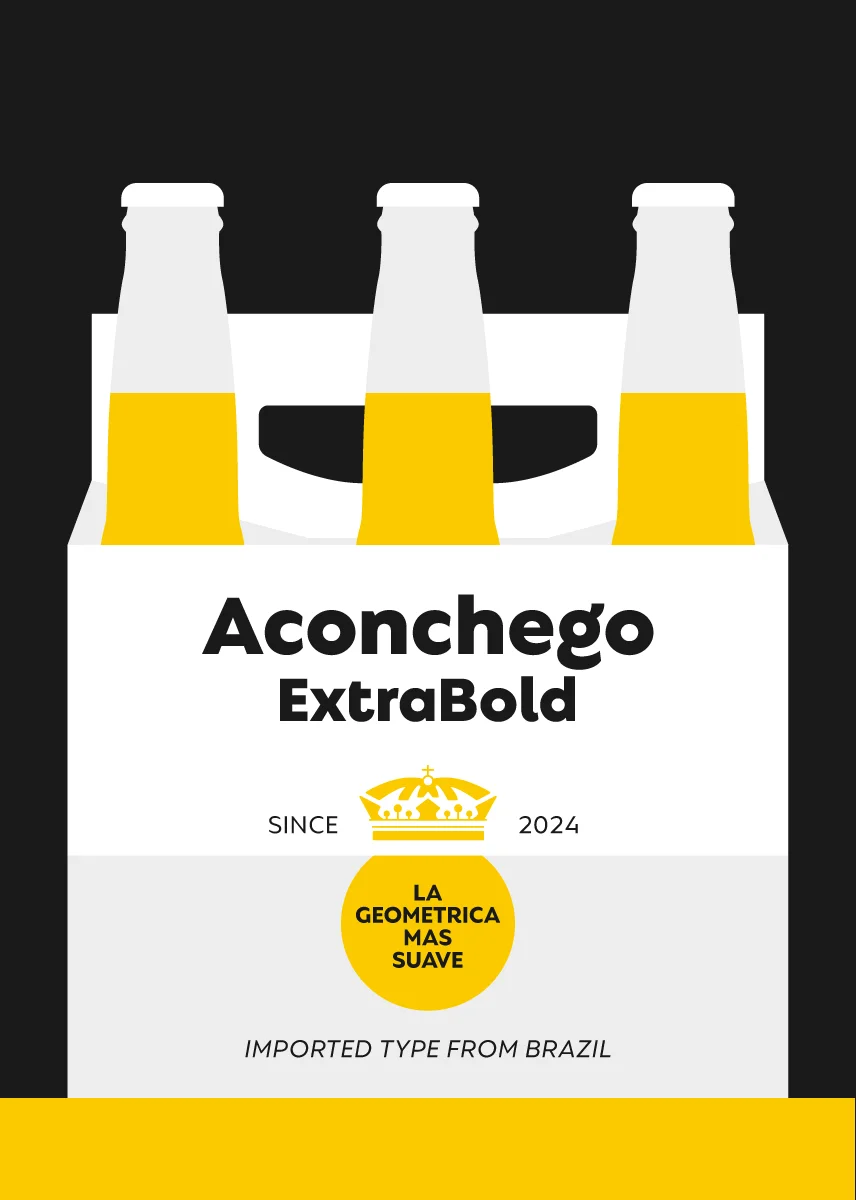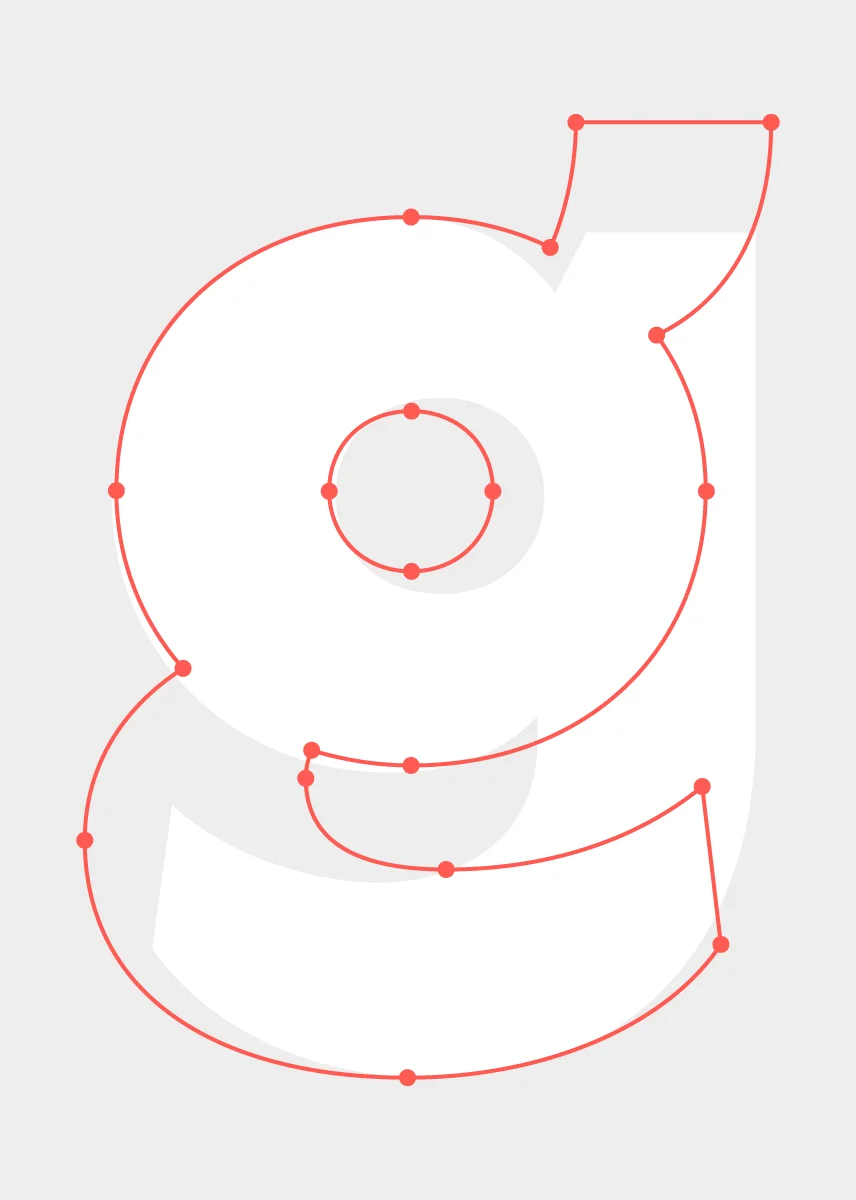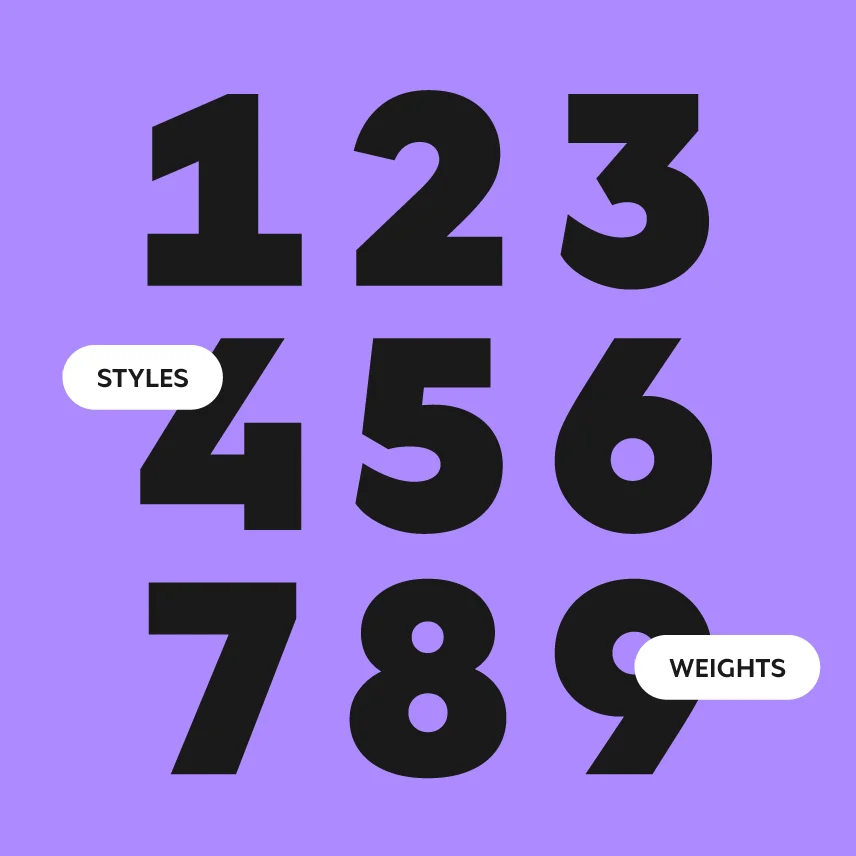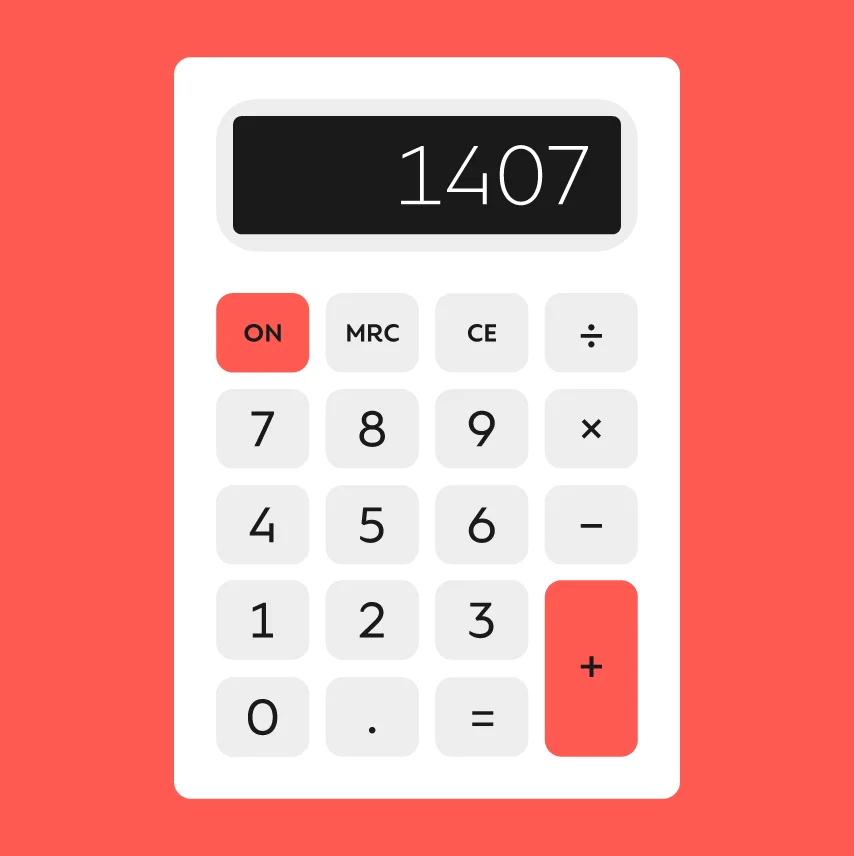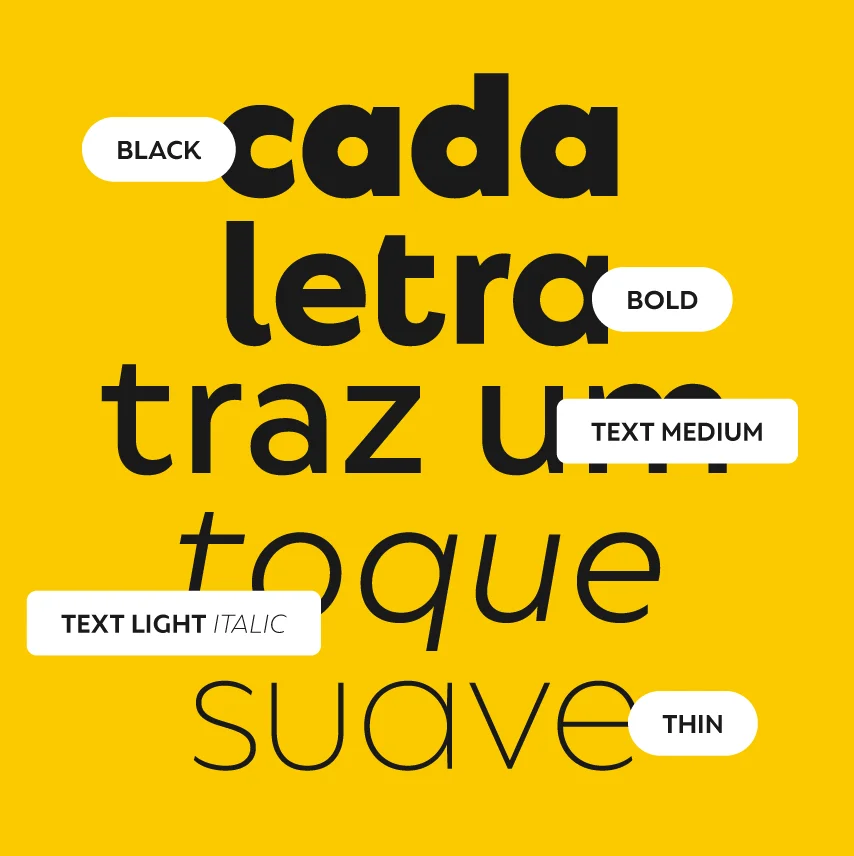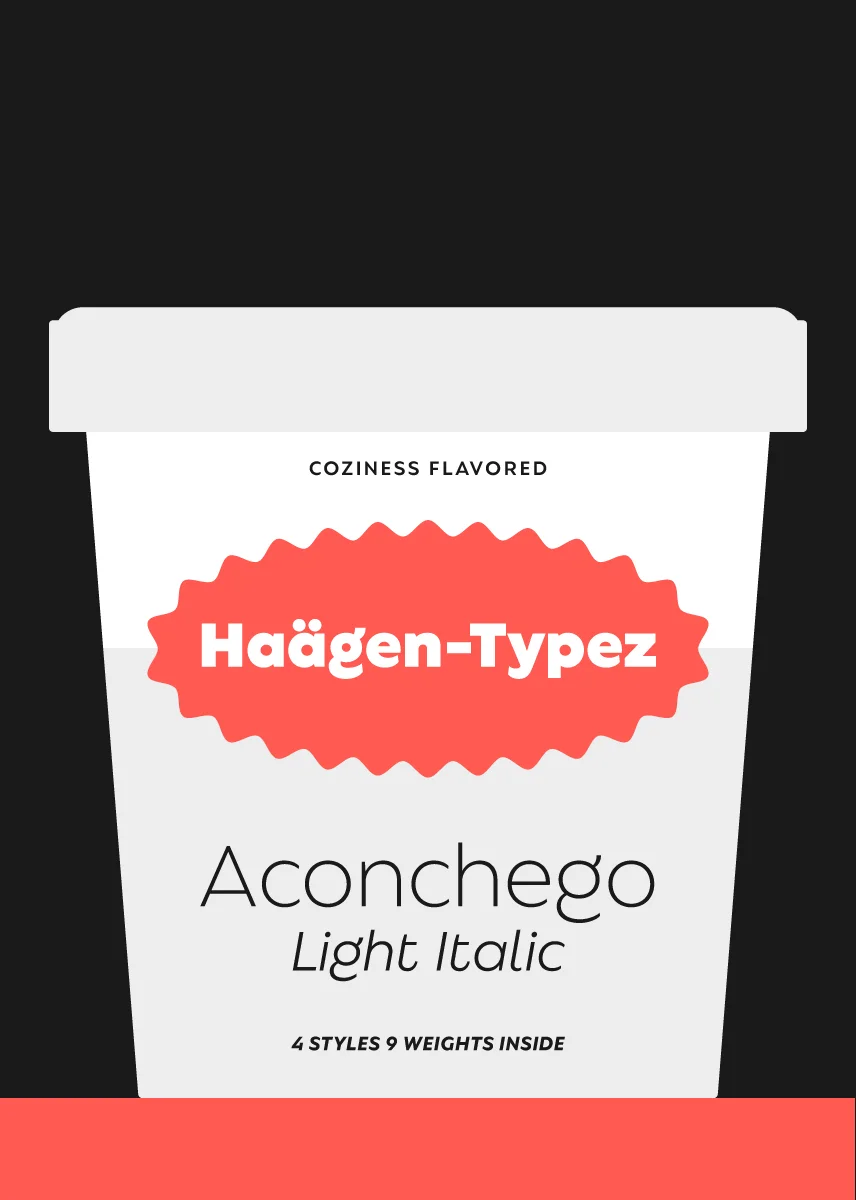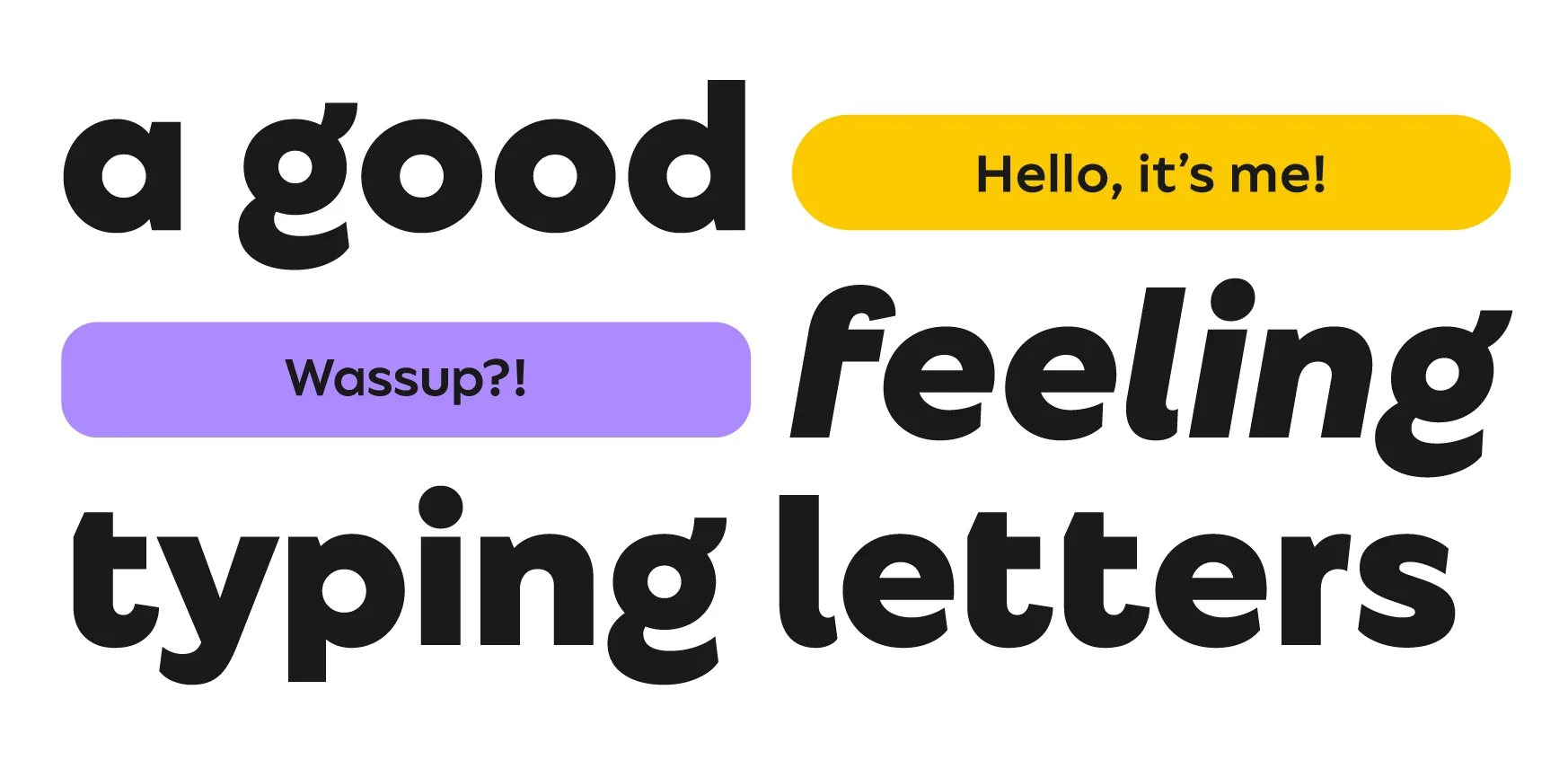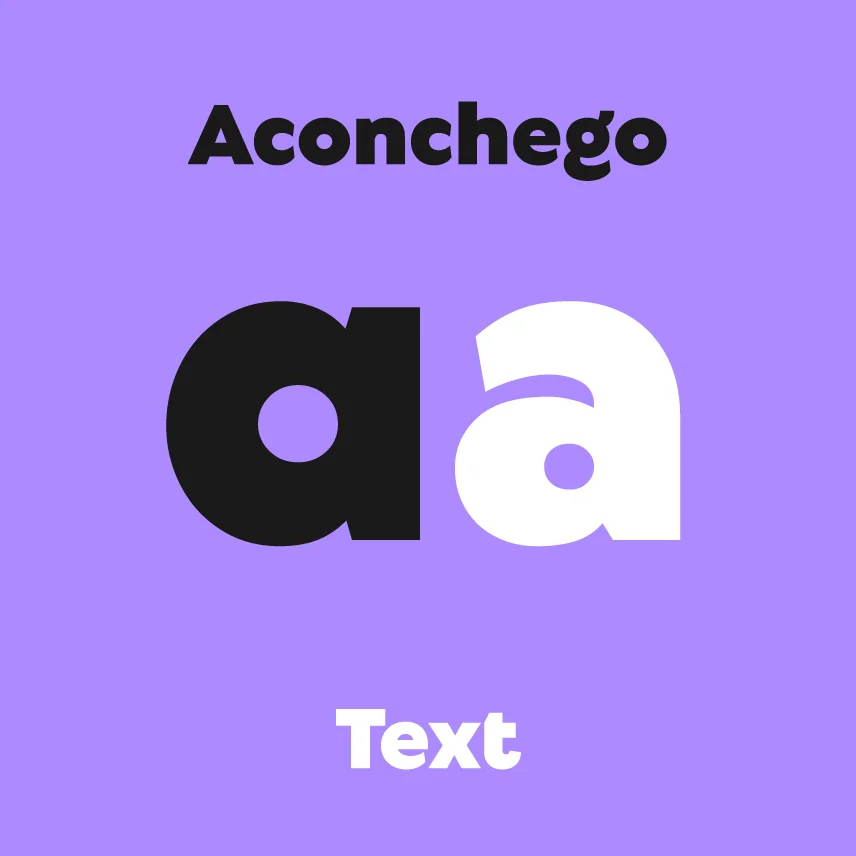
Aconchego
Where the good vibes meet
Um toque de aconchego cabe em todo lugar
Ah. Com. Chegar.
Me conta: qual é o seu livro favorito?
Mucho Relaxo
In a free afternoon of crossword puzzles accompanying ocean waves. In a long conversation with your best friend. In a poster with beautiful words in your favorite neighborhood.
Who brings coziness to your life?
Functionally relaxing
Looooooong conversations in the sand.
Que bom que você veio
Pra onde você pode levar mais aconchego?
2024
9
4
Suporte a 209 idiomas do sistema de escrita Latino.
O que é aconchego pra você?
(ah. com. chegar.)
O conforto que encontra os eixos.
A leveza que aproxima os traços.
O charme que acentua as formas.
É um encontro que abre aspas para boas sensações.
“Chega mais.”
“Que surpresa boa.”
“Que bom que você veio.”
Pra gente, um toque de aconchego cabe em todo lugar.
Em uma tarde livre de palavras cruzadas acompanhando as ondas do mar.
Em uma conversa demorada com o seu melhor amigo.
Em um cartaz com palavras bonitas no seu bairro favorito da cidade.
Se tudo pode ser aconchegante, por que não convidar as boas sensações para uma tipografia?
Encontros geometricamente aconchegantes.
Formas funcionalmente relaxantes.
Caracteres flexivelmente suaves.
Traços essencialmente confortáveis.
Tipos contemporaneamente gentis.
Ah, que coisa boa.
Com espaço para um toque único, versátil e próprio, de A a Z.
Já que é pra acentuar os encontros, queremos te fazer um convite:
Pra onde você pode levar mais aconchego?